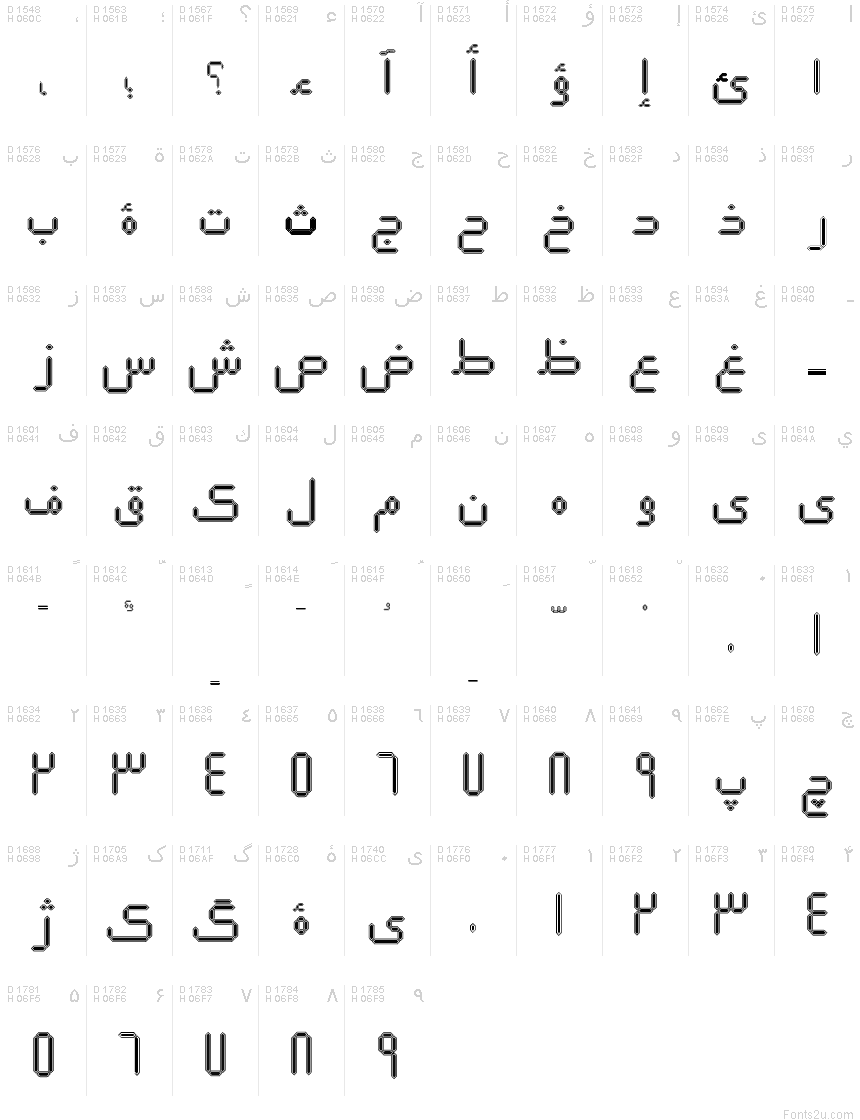
B Elm Border di Borna Rayaneh è un font arabo gratuito di tipo display, ispirato al look segmentato dei pannelli LED e delle insegne elettroniche, adattando questa logica alle forme delle lettere arabe. La costruzione contornata e le spaziature uniformi creano un ritmo tecnico preciso, conferendo ai caratteri l'aspetto di un display digitale piuttosto che quello di una calligrafia tradizionale.
Il suo carattere elettronico la rende una scelta naturale per il branding tecnologico, la grafica di interfacce, la visualizzazione di videogiochi, poster per eventi e packaging a tema digitale che richiedono un inconfondibile stile "schermo". Il font è inoltre una risorsa gratuita affidabile per titoli in arabo, cartelli e brevi testi che traggono vantaggio dalla sua struttura pulita e segmentata.